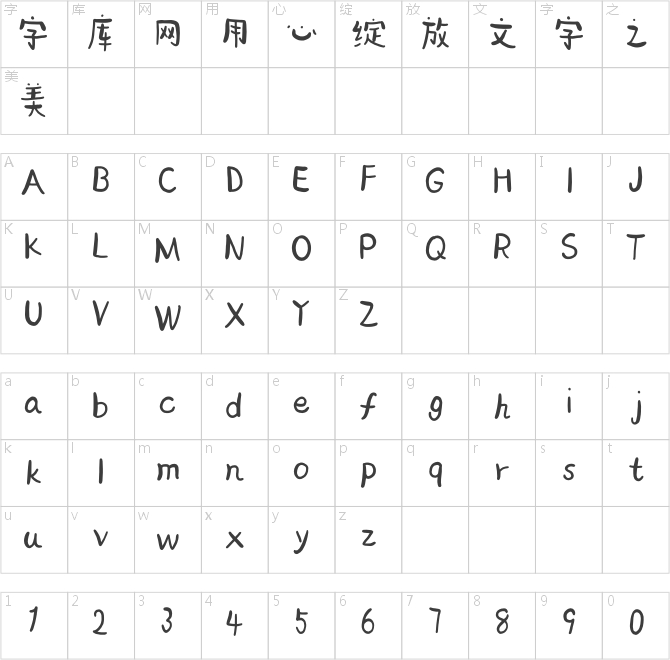
造字工房新俏體,結(jié)體松散恣意,筆畫(huà)處理不拘一格,個(gè)性突出。整體效果靈妙幼拙、天真可愛(ài),極生動(dòng)之致。適用于兒童讀物、報(bào)刊雜志標(biāo)題、廣告設(shè)計(jì)、個(gè)性招牌等視覺(jué)環(huán)境,有著極強(qiáng)的應(yīng)用空間。本字體為簡(jiǎn)體字庫(kù),采用OpenType/CID格式,Adobe-GB1-5編碼。基于中華人民共和國(guó)GB2312-80字符集標(biāo)準(zhǔn),另按需添加101個(gè)漢字。共收容字?jǐn)?shù)6864CJK漢字,ASCII常用字符100個(gè)。